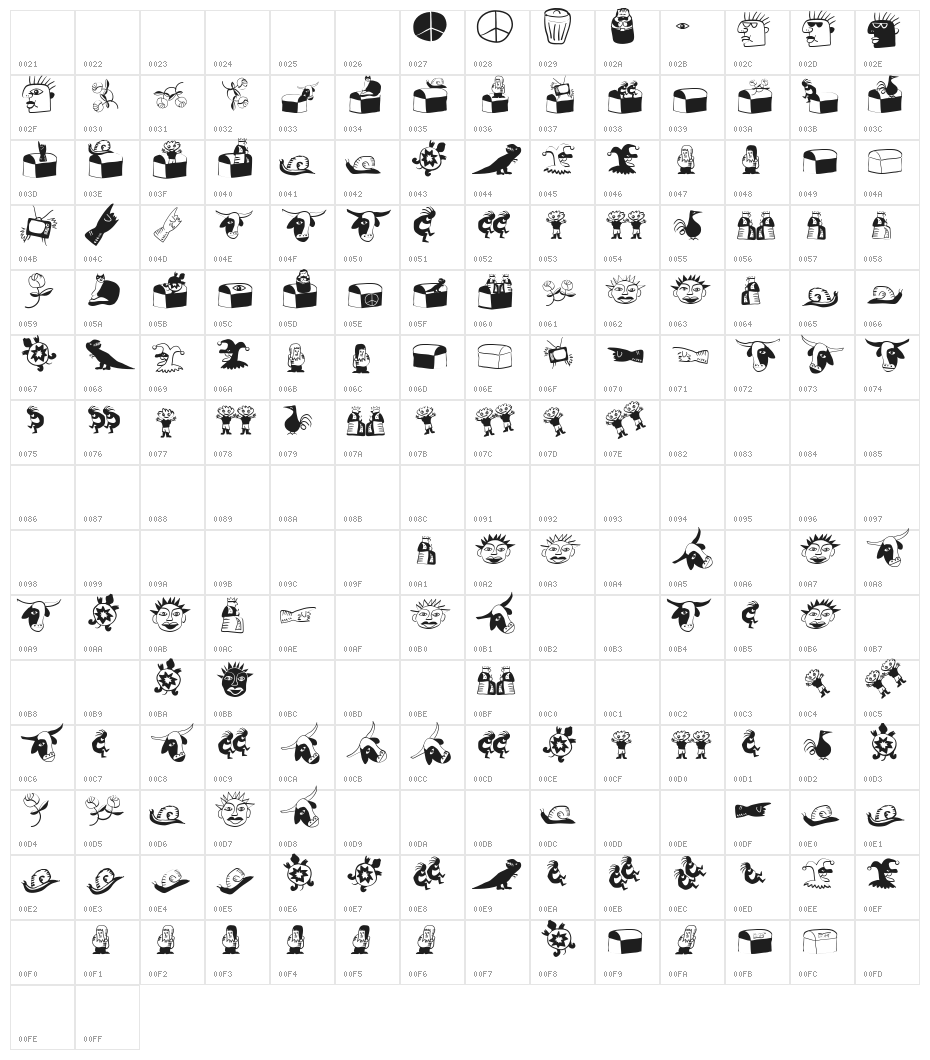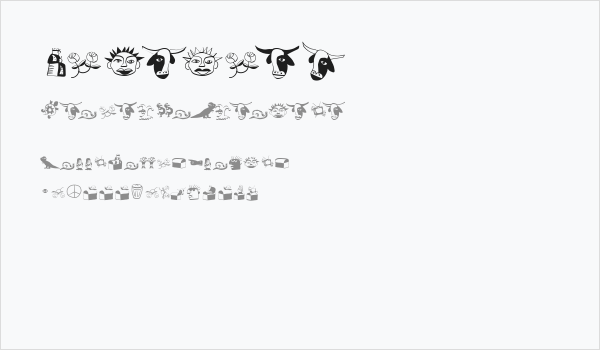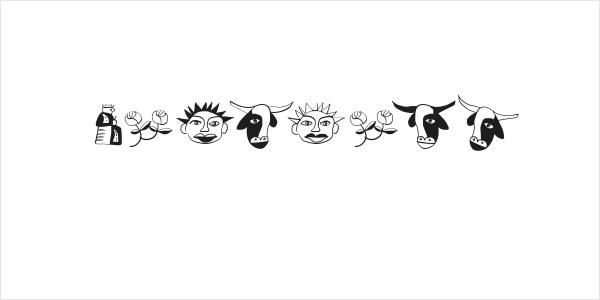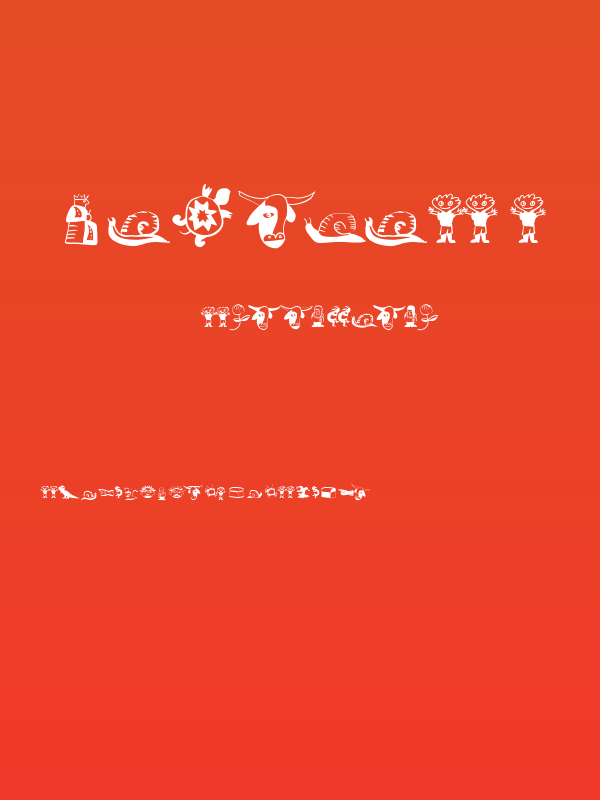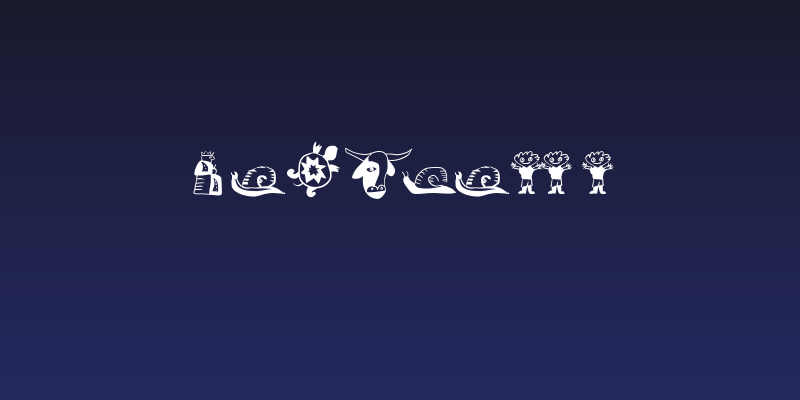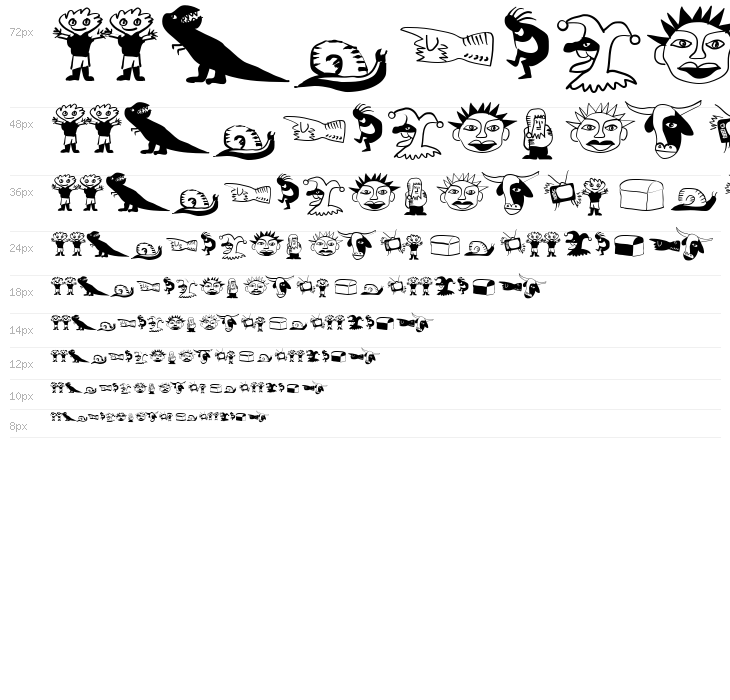
WacObats Font
| Caso d'uso | Logos, Posters, Artistic projects |
| Progetti proposti | Ideal for children's books, creative posters, artistic branding, and any project requiring a fun and imaginative touch. |